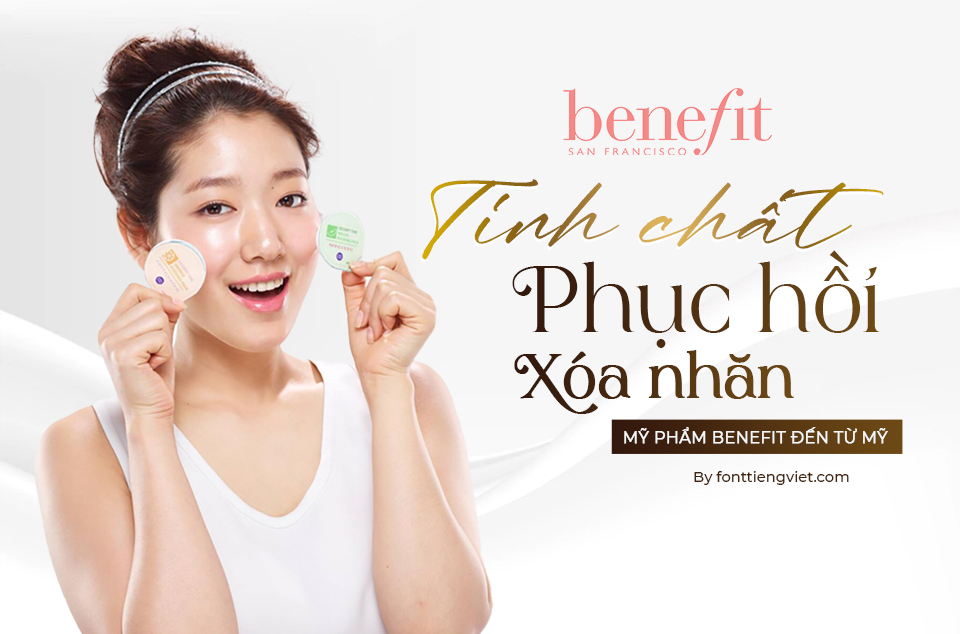
Combo font thiết kế Spa, mỹ phẩm 1 – Kèm file Ps chứa hiệu ứng
Combo font thiết kế Spa, mỹ phẩm 1 – Kèm file Ps chứa hiệu ứng chuyên nghiệp
Giới thiệu bộ Combo font thiết kế Spa, mỹ phẩm 1 – Kèm file Ps chứa hiệu ứng
Trong lĩnh vực làm đẹp, việc lựa chọn Font Miễn Phí phù hợp đóng vai trò then chốt để truyền tải sự sang trọng và tinh tế. Bộ Combo font thiết kế Spa, mỹ phẩm 1 – Kèm file Ps chứa hiệu ứng được xây dựng nhằm giúp các nhà thiết kế tối ưu hóa quy trình làm việc. Không chỉ dừng lại ở các ký tự đơn thuần, bộ công cụ này mang đến giải pháp toàn diện cho bộ nhận diện thương hiệu từ logo đến banner quảng cáo. Sự kết hợp giữa các đường nét mềm mại và cấu trúc hiện đại giúp tôn vinh giá trị của từng sản phẩm mỹ phẩm hay dịch vụ spa cao cấp. Đây là lựa chọn lý tưởng cho những ai đang tìm kiếm sự khác biệt trong phong cách thiết kế đồ họa tại Việt Nam hiện nay.
Đặc điểm nổi bật của Combo font thiết kế Spa, mỹ phẩm 1 – Kèm file Ps chứa hiệu ứng
Sự đa dạng trong phong cách chữ
Bộ combo này tập hợp những mẫu chữ được tuyển chọn kỹ lưỡng, từ phong cách Serif cổ điển đến Script uyển chuyển. Mỗi phông chữ đều được Việt hóa hoàn chỉnh, đảm bảo không lỗi dấu khi đánh văn bản tiếng Việt. Điều này đặc biệt quan trọng khi bạn cần trình bày các thông tin chi tiết về thành phần mỹ phẩm hoặc bảng giá dịch vụ spa. Những nét chữ thanh mảnh gợi lên cảm giác thư thái, trong khi các nét đậm lại tạo điểm nhấn mạnh mẽ cho các chương trình khuyến mãi lớn.
Tiện ích từ file Photoshop đi kèm
Điểm giá trị nhất của Combo font thiết kế Spa, mỹ phẩm 1 – Kèm file Ps chứa hiệu ứng chính là tệp tin định dạng Photoshop (.psd) tích hợp sẵn các Layer Style độc đáo. Người dùng không cần tốn quá nhiều thời gian để tự tạo các hiệu ứng đổ bóng, ánh kim (gold leaf) hay hiệu ứng chữ nổi 3D. Mọi thứ đã được thiết lập sẵn trong các Smart Object, cho phép bạn chỉ cần thay đổi nội dung chữ là hiệu ứng sẽ tự động áp dụng. Điều này giúp nâng tầm thẩm mỹ cho bản thiết kế chỉ trong vài cú nhấp chuột đơn giản.
Ứng dụng thực tế của bộ font trong ngành làm đẹp
Thiết kế bao bì và nhãn mác mỹ phẩm
Sử dụng bộ font này giúp các thương hiệu mỹ phẩm nội địa trông chuyên nghiệp và bắt mắt hơn trên kệ hàng. Các font chữ trong bộ combo được tối ưu để in ấn trên nhiều chất liệu khác nhau từ chai thủy tinh đến hộp giấy. Độ tương phản cao và khoảng cách chữ hợp lý giúp khách hàng dễ dàng đọc được thông tin sản phẩm dù ở kích thước nhỏ. Sự đồng bộ giữa phông chữ và hiệu ứng Ps đi kèm tạo nên một diện mạo đẳng cấp, giúp tăng khả năng nhận diện thương hiệu hiệu quả.
Xây dựng hình ảnh quảng cáo trên mạng xã hội
Đối với các tiệm Spa hay thẩm mỹ viện, hình ảnh trên Facebook hay Instagram chính là bộ mặt của doanh nghiệp. Tận dụng Combo font thiết kế Spa, mỹ phẩm 1 – Kèm file Ps chứa hiệu ứng sẽ giúp các bài đăng của bạn thu hút ánh nhìn ngay lập tức. Những hiệu ứng chữ lấp lánh hoặc đổ bóng mịn màng tạo cảm giác sạch sẽ và chuyên nghiệp. Bạn có thể dễ dàng tạo ra các mẫu Story hấp dẫn hoặc các banner website đồng nhất về mặt thị giác, giúp khách hàng cảm nhận được sự chu đáo ngay từ lần đầu tiếp xúc.
Kết luận về bộ sưu tập font chữ cao cấp